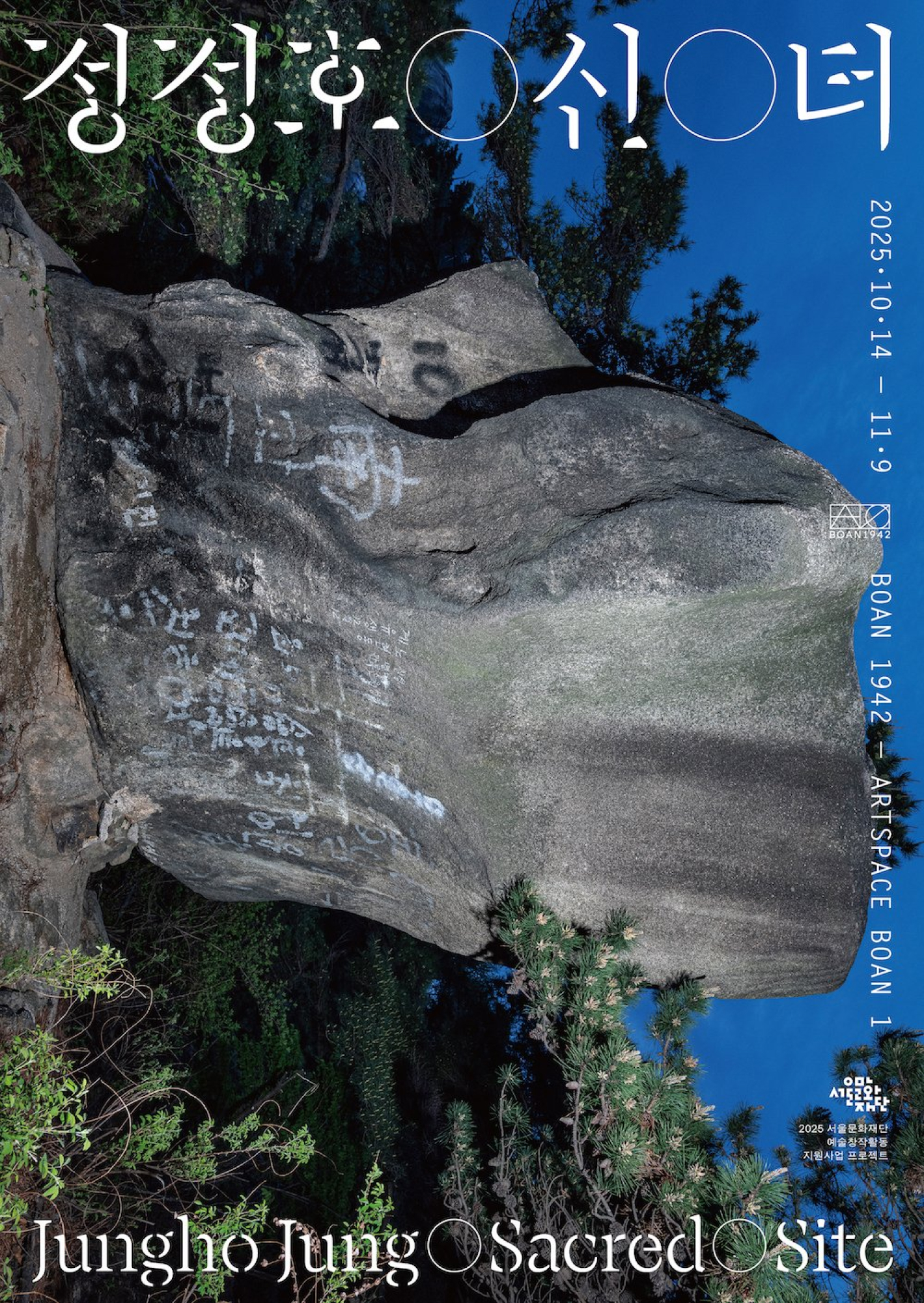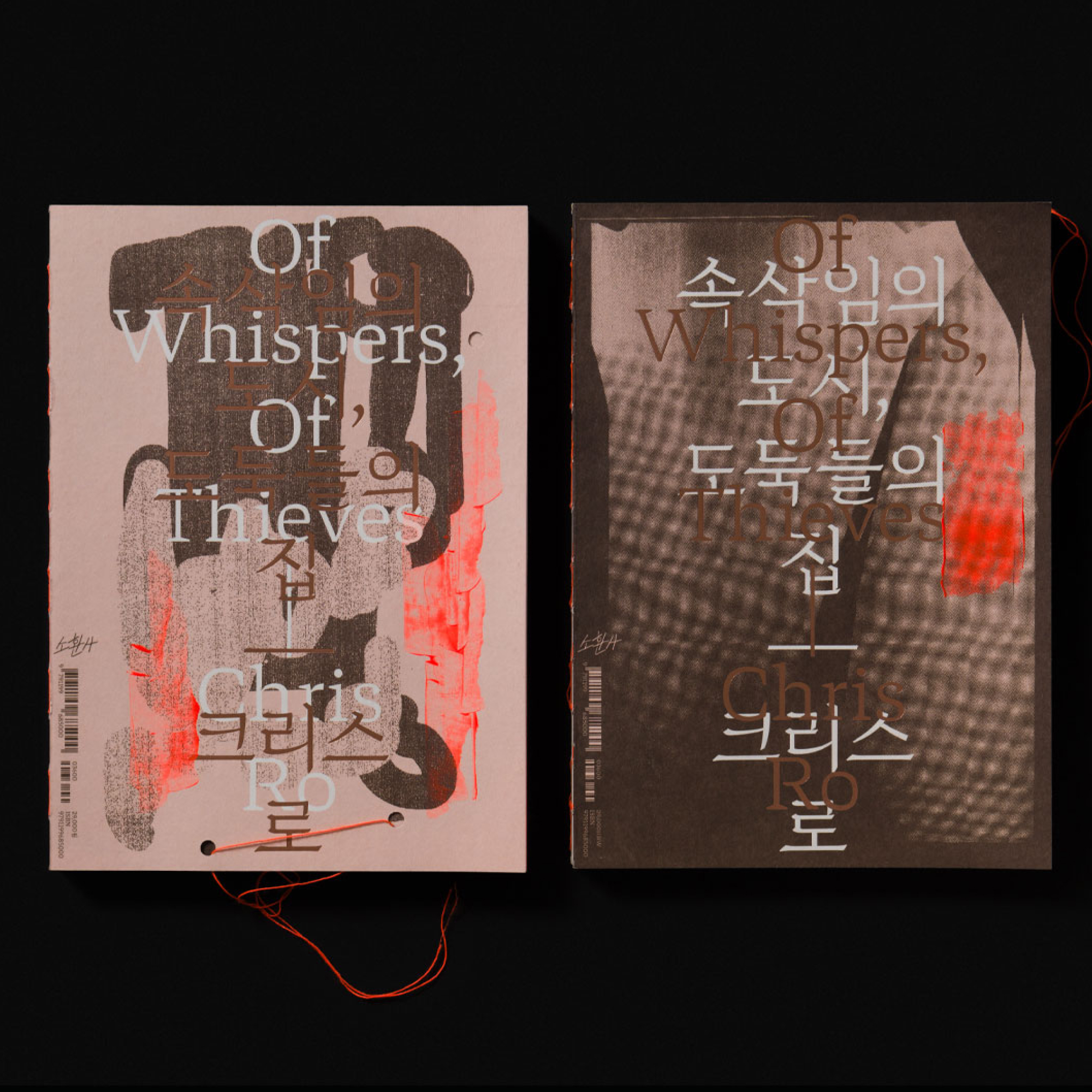
반야(Banya)는 전통적인 붓글씨와 목판을 새김을 혼합한 한글 부리계열 글꼴입니다. 이 서체는 20세기 초에 목판본으로 출판된 것으로 추정되는 한 불경에서 영감을 얻어 만들게 된 서체입니다. 전반적으로 나무에 새겨져 샤프하고 단단함 느낌이 듬과 동시에 붓의 쓰임도 같이 느껴져서 섬세하고 독특한 형상을 자아냅니다. 예로들면, 이응의 형태는 마치 붓으로 이어쓴 느낌을 강조한 반면에, 디귿이나 미음에서는 새김의 형태를 도드라지게 하기위해 살짝 스텐실적인 느낌을 가미했습니다. 반야 미스트(Banya Mist)는 반야 오리지널이 가진 형태를 유지한채 일부 형태가 사라지는 형상을 띄고 있는 스텐실계열 디스플레이형 글꼴입니다. ‘반야’가 깨달음의 경지에 이른 초월적 지혜를 뜻하는 거라면, 그 경지의 다다름은 마치 보이지 않는 안개와 같은 느낌이라고 생각했습니다. 반야가 목판본 불경에서 나타난 글자의 형태에서 영감을 받은 것이라면, 반야 미스트는 진리는 안개에 가려져 보이지 않는 듯한 느낌을 글자 형태에 담아보고자 했습니다.
이노을
Noheul Lee
국민대학교 대학원 커뮤니케이션 디자인 석사과정과 네덜란드 헤이그 왕립 예술학교(KABK) 타입미디어(TypeMedia) 석사과정을 졸업했다. 현재 한글, 라틴 중심의 글꼴 디자이너로 활동 중이다. 제6회 방일영문화재단 글꼴창작지원사업에 선정되었고, 2019년도 일본 모리사와 타입 공모전 라틴 카테고리에서 금상을 받았다. 현재 로리스 올리비에와 글꼴 제작 스튜디오인 lo-ol type studio를 운영 중이다. 대표 글꼴로는 아리온(Areon), 아르바나(Arvana), 기파란(Giparan), 오흐탕크(Ortank) 등이 있다.
기파란의 이름 배경은 생각보다 단순하다. 한국인이라면 누구나 쉽게 떠오를 신라시대 화랑의 이름 ‘기파랑’에서 따온 것이다. 젊은 화랑이 지닌 열정적이고 도전적인 모습과 인자한 성품의 느낌이 글자의 인상과 어울린다고 생각했다. 살짝 넓은 너비의 수직 수평의 민부리형 구조는 젊은 무사의 기개를, 부리의 디테일과 중간중간의 부드러운 휴머니스트적 터치는 화랑의 인품을 표현해보고자 했다. 이름을 특별히 살짝 변경한데는 이유가 있다. 한자음을 해석하자면 랑은 사내를 칭한 것인데 제작자로써 서체에 성별을 더하고 싶지 않았기 때문이다. 란으로 바꿔 단어 그대로 ‘파란’이라는 단어가 더 느낌적으로 잘 어울린다는 판단이 들었다.
‘오흐탕크(Ortank) 한글 텍스트 / 디스플레이’는 지오매트릭 그로테스크 계열의 서체로 기하학적 형태의 한계를 탐구한 결과물인 오흐탕크 텍스트(Ortank Text), 오흐탕크 디스플레이 (Ortank Display)의 한글 버전입니다. 직선형 그로테스크 스타일에서 오는 약간의 고전적인 느낌에 단순함이 결합되었습니다.